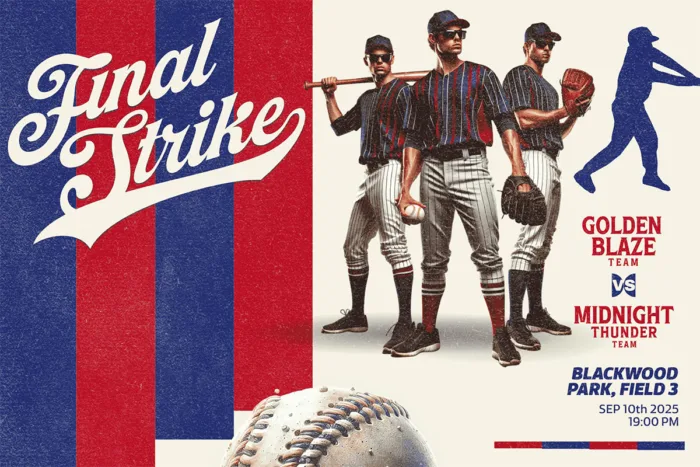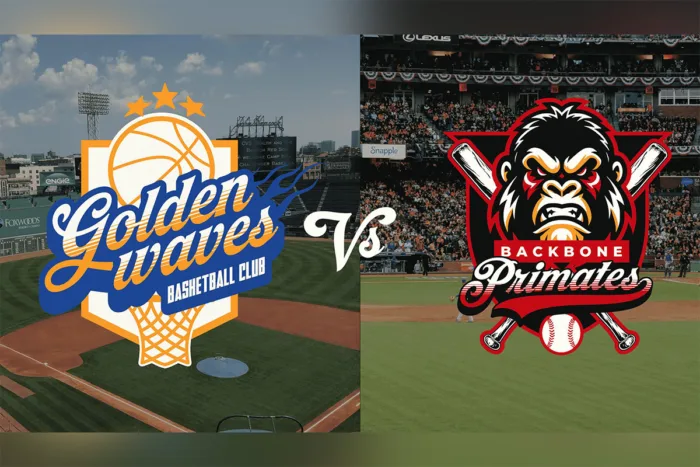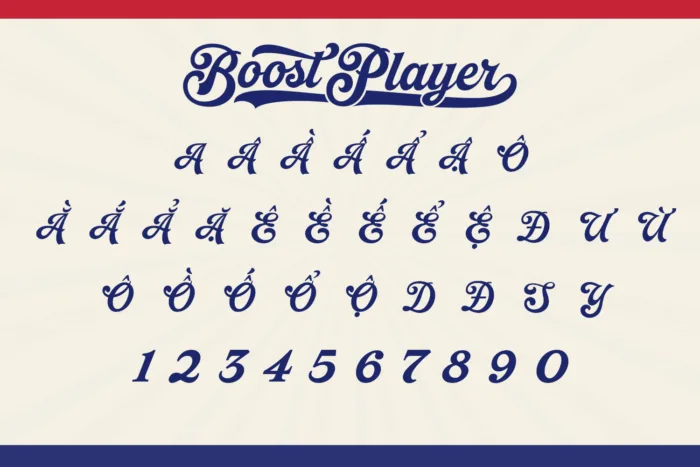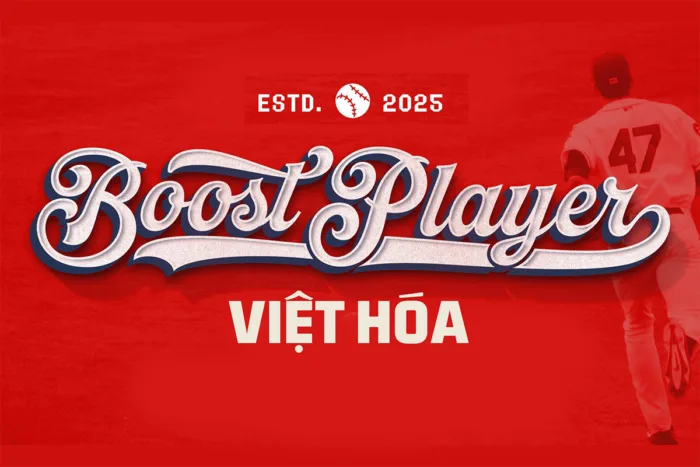
DVN Boost Player Việt hóa – Bản đủ bộ số và nâng cấp kiểu chữ
Boost Player là một font chữ script cổ điển, mang phong cách hoài cổ kết hợp với sự mạnh mẽ, lý tưởng cho thiết kế logo, thương hiệu thể thao và các dự án typography đậm chất vintage. Với những đường nét uyển chuyển nhưng không kém phần khỏe khoắn, Boost Player gợi nhớ đến các biểu tượng bóng chày, bóng bầu dục của những năm 80-90.
Font chữ này nổi bật với hiệu ứng 3D đổ bóng dày, tạo chiều sâu và cảm giác năng động. Sự kết hợp giữa nét chữ mềm mại cùng đường viền sắc nét giúp Boost Player dễ dàng áp dụng cho nhiều phong cách thiết kế khác nhau.
Dù bạn đang tìm kiếm một kiểu chữ cho áo đấu, poster sự kiện thể thao hay thương hiệu cá nhân, Boost Player sẽ mang đến sự chuyên nghiệp, hoài cổ nhưng vẫn đầy sức sống. Đây là lựa chọn hoàn hảo cho những ai yêu thích phong cách lettering cổ điển và mạnh mẽ.
Phiên bản Việt hóa đã đầy đủ bộ số và kiểu chữ được fix lại để phù hợp hơn.